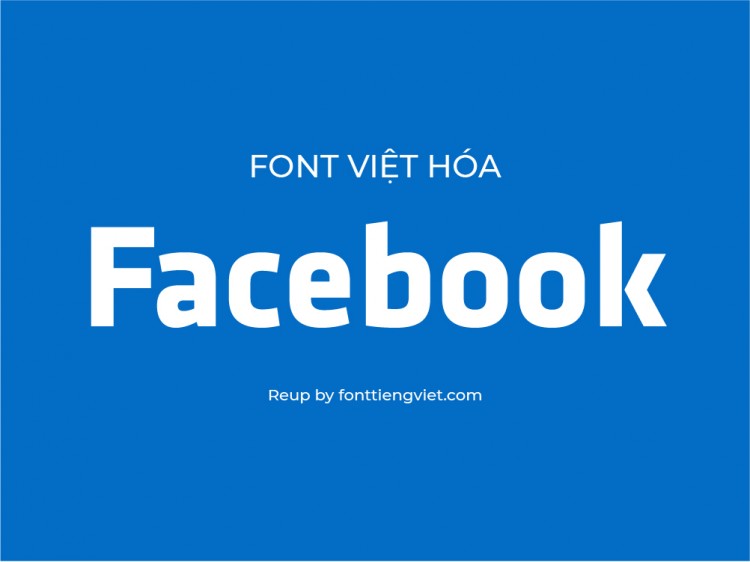
Font việt hóa UTM Facebook trong logo facebook
Font việt hóa UTM Facebook trong logo facebook: Giải pháp thiết kế hoàn hảo cho bạn
Trong lĩnh vực thiết kế đồ họa hiện nay, việc lựa chọn Font Miễn Phí phù hợp đóng vai trò then chốt giúp nhận diện thương hiệu hiệu quả. Đặc biệt, cụm từ Font việt hóa UTM Facebook trong logo facebook luôn được các nhà thiết kế săn đón bởi sự tương đồng kỳ lạ với kiểu chữ biểu tượng của mạng xã hội lớn nhất thế giới. Bộ phông này không chỉ mang lại vẻ ngoài hiện đại, tối giản mà còn đảm bảo tính thẩm mỹ cao khi ứng dụng vào các sản phẩm truyền thông tại Việt Nam.
Sức hút của Font việt hóa UTM Facebook trong logo facebook
Bộ font này thực tế được tùy biến dựa trên các đặc điểm của kiểu chữ Klavika, vốn nổi tiếng với những đường nét gãy gọn và mạnh mẽ. Việc sử dụng Font việt hóa UTM Facebook trong logo facebook giúp người dùng dễ dàng tạo ra các ấn phẩm có độ nhận diện cao. Đối với các bạn học sinh và sinh viên, đây là công cụ đắc lực để thiết kế slide thuyết trình, làm poster sự kiện hay tạo logo cá nhân mang phong cách công nghệ chuyên nghiệp.
Ưu điểm khi sử dụng font chữ trong thiết kế học đường
Lợi ích lớn nhất của phiên bản việt hóa này chính là khả năng hiển thị tiếng Việt hoàn hảo, không bị lỗi dấu hay sai lệch định dạng. Các nét chữ đều đặn giúp văn bản trở nên dễ đọc, phù hợp với tiêu chuẩn giáo dục và trình bày văn bản trang trọng. Hơn nữa, tính tương thích cao với các phần mềm đồ họa như Photoshop hay Illustrator giúp việc sáng tạo trở nên mượt mà hơn bao giờ hết.